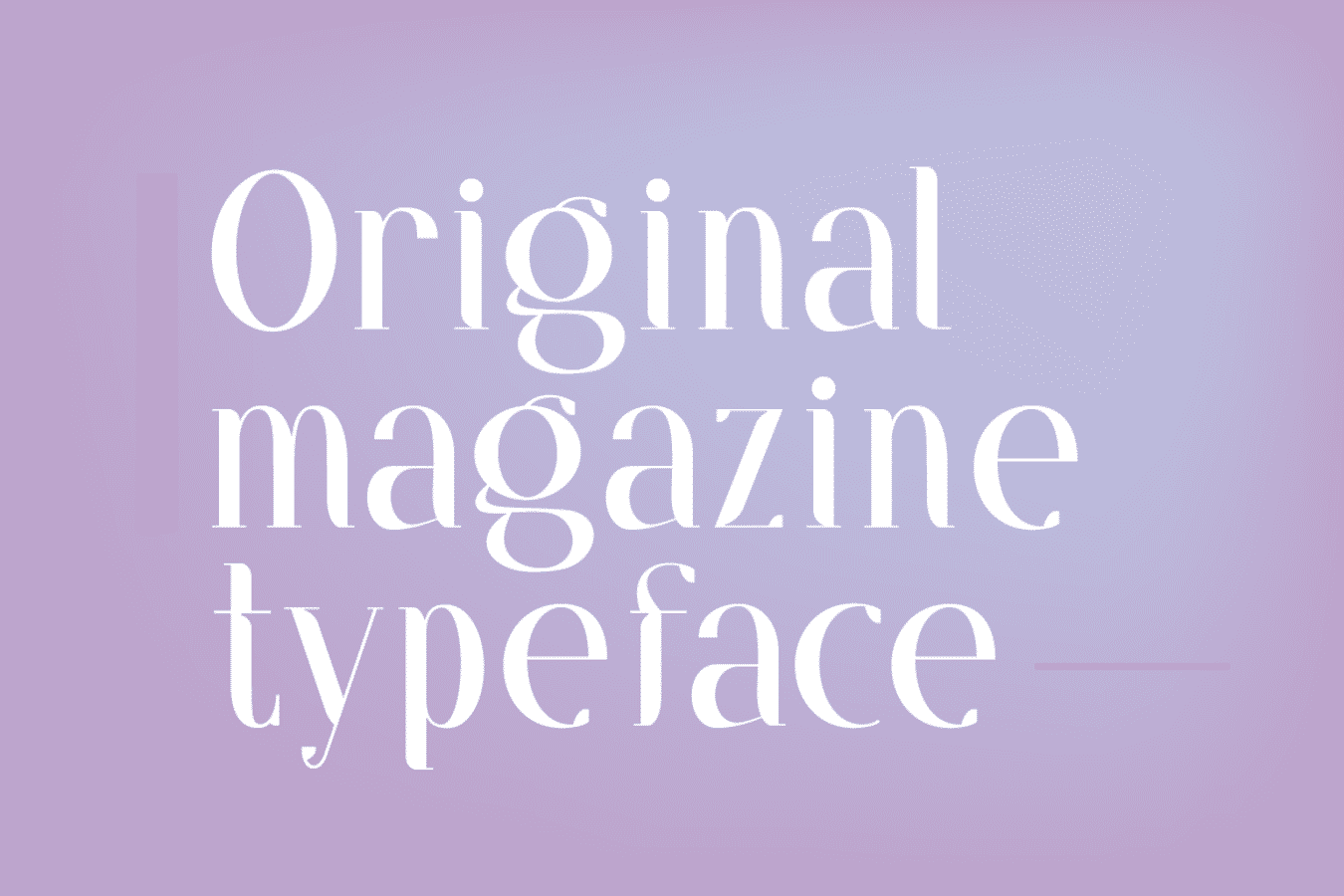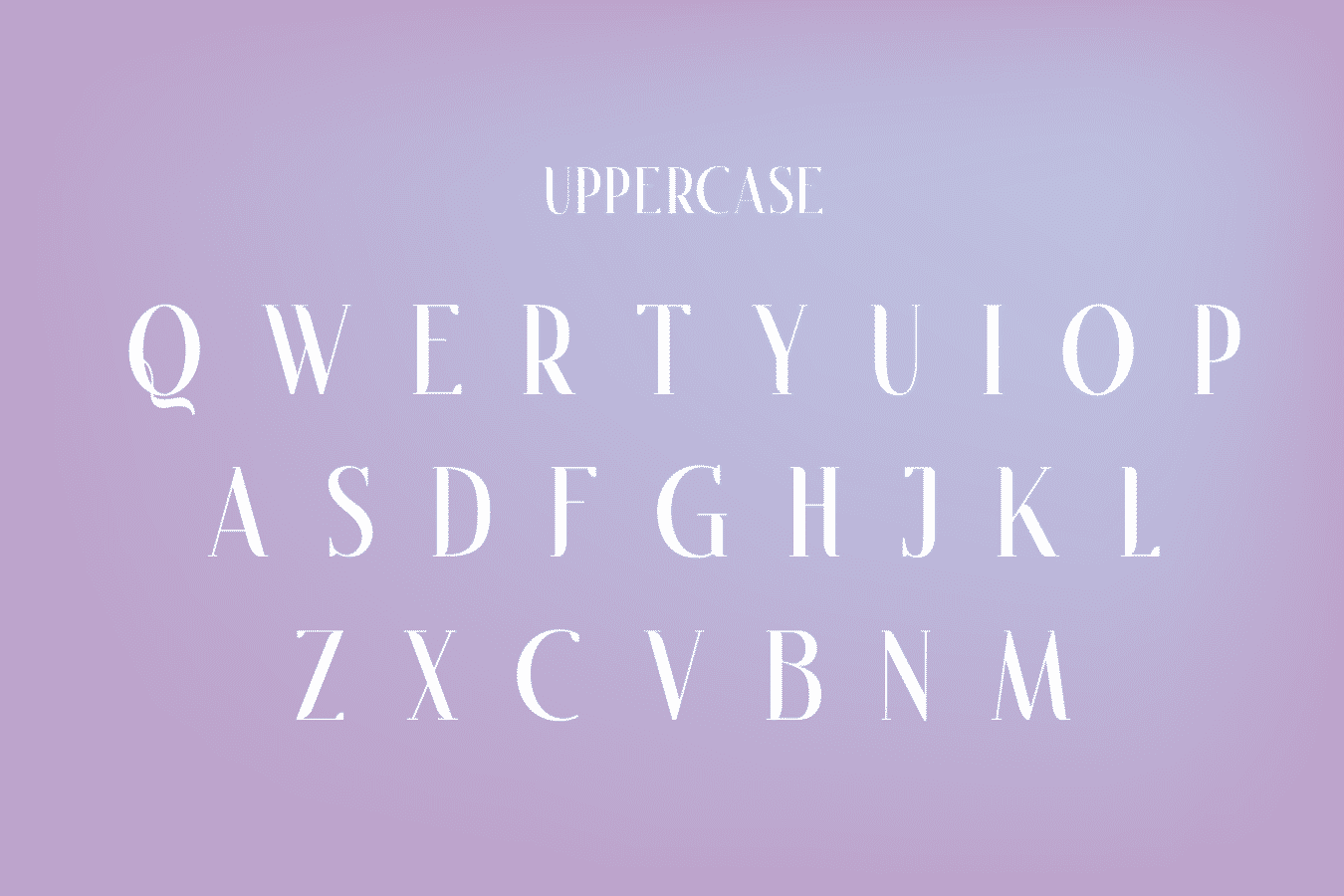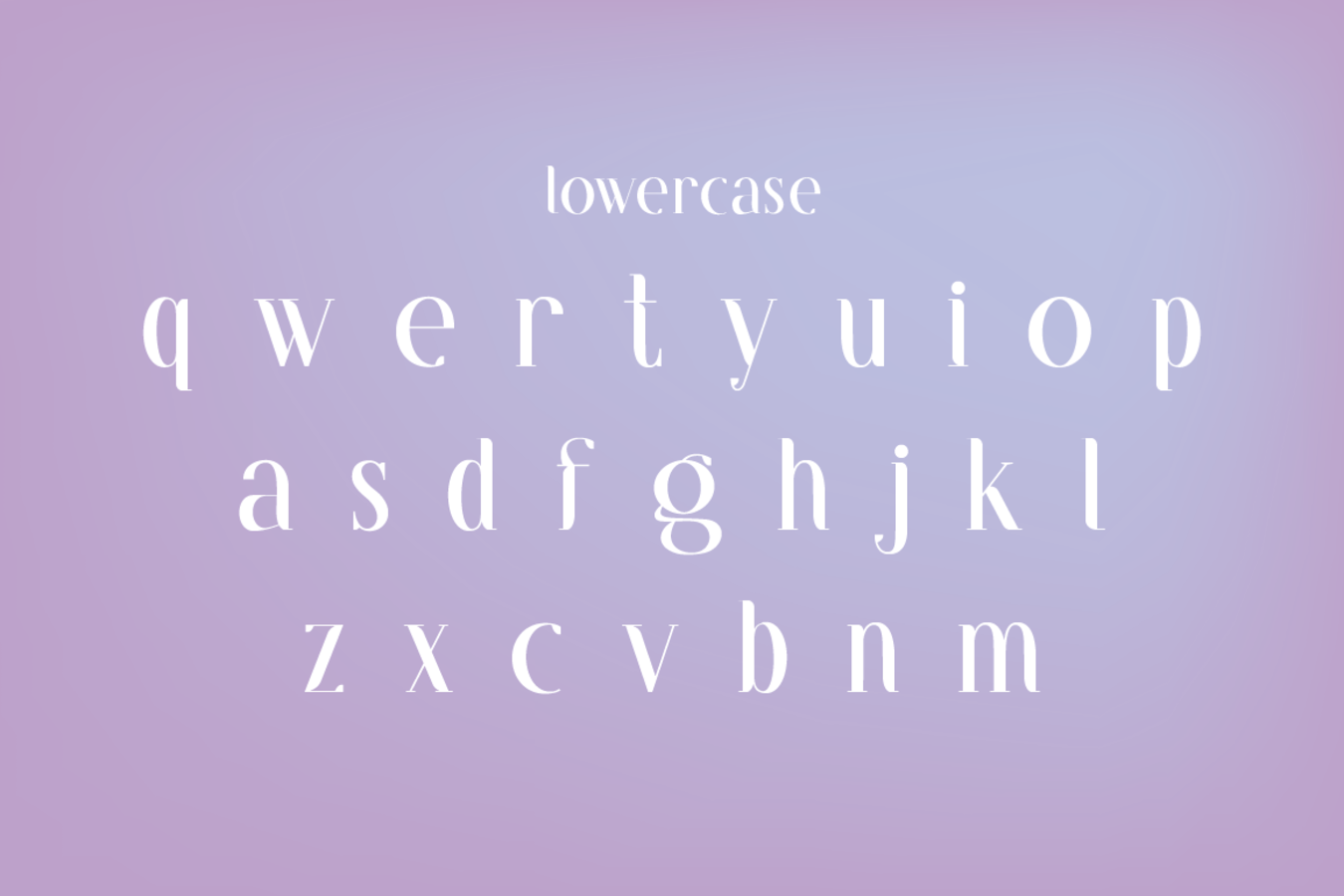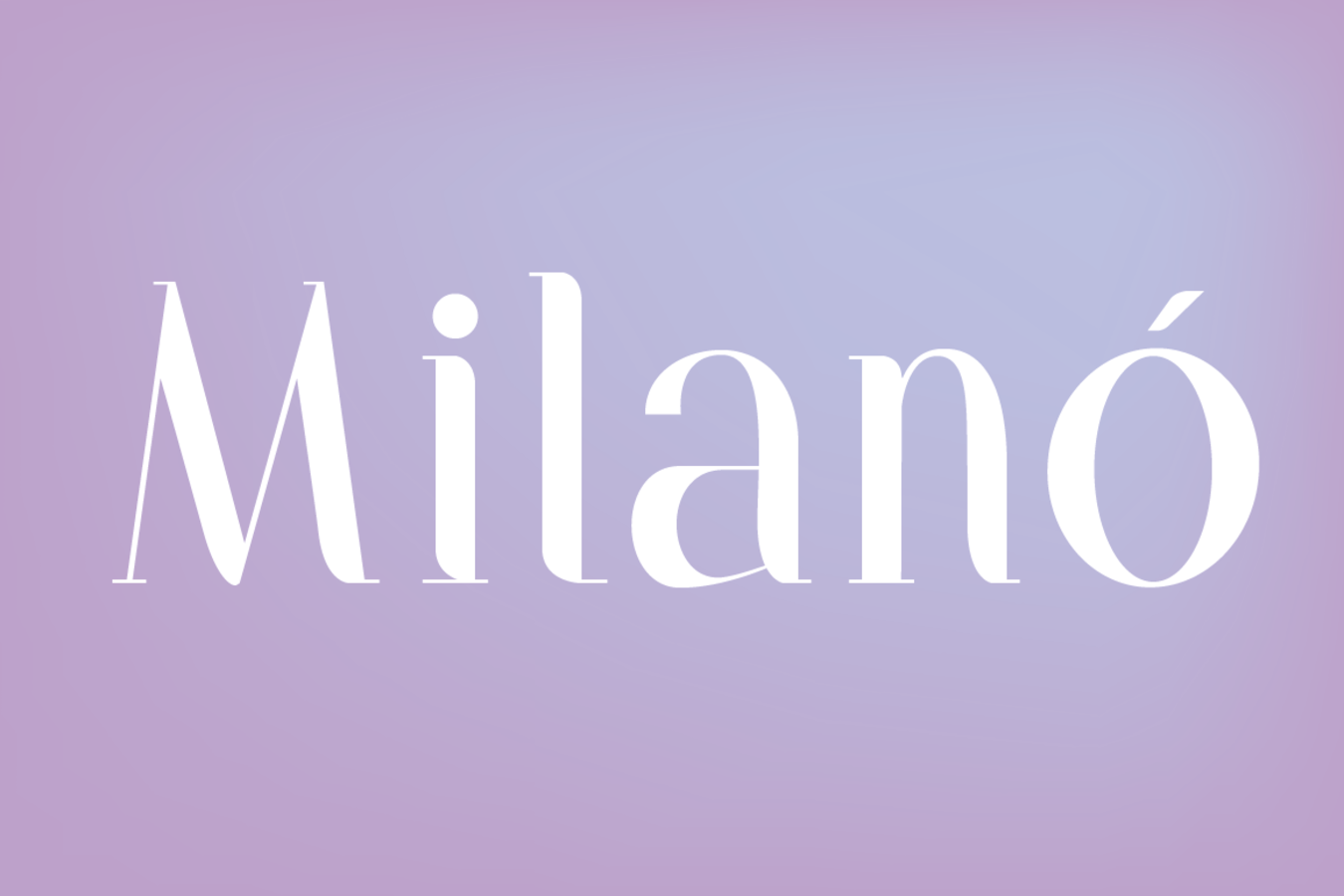
强大而令人印象深刻的时尚字体设计,Yaarve字体
Strong & impressively stylish typeface design, Yaarve Typeface
引入令人兴奋的新字体添加到您的收藏中! Yaarve展示了时尚设计的强大而富有表现力的角色,非常适合打印和网页设计。它包括标准连字,1500+的字距调整,拉丁字母和变音符号。我希望你在即将到来的美好工作中对你有用!